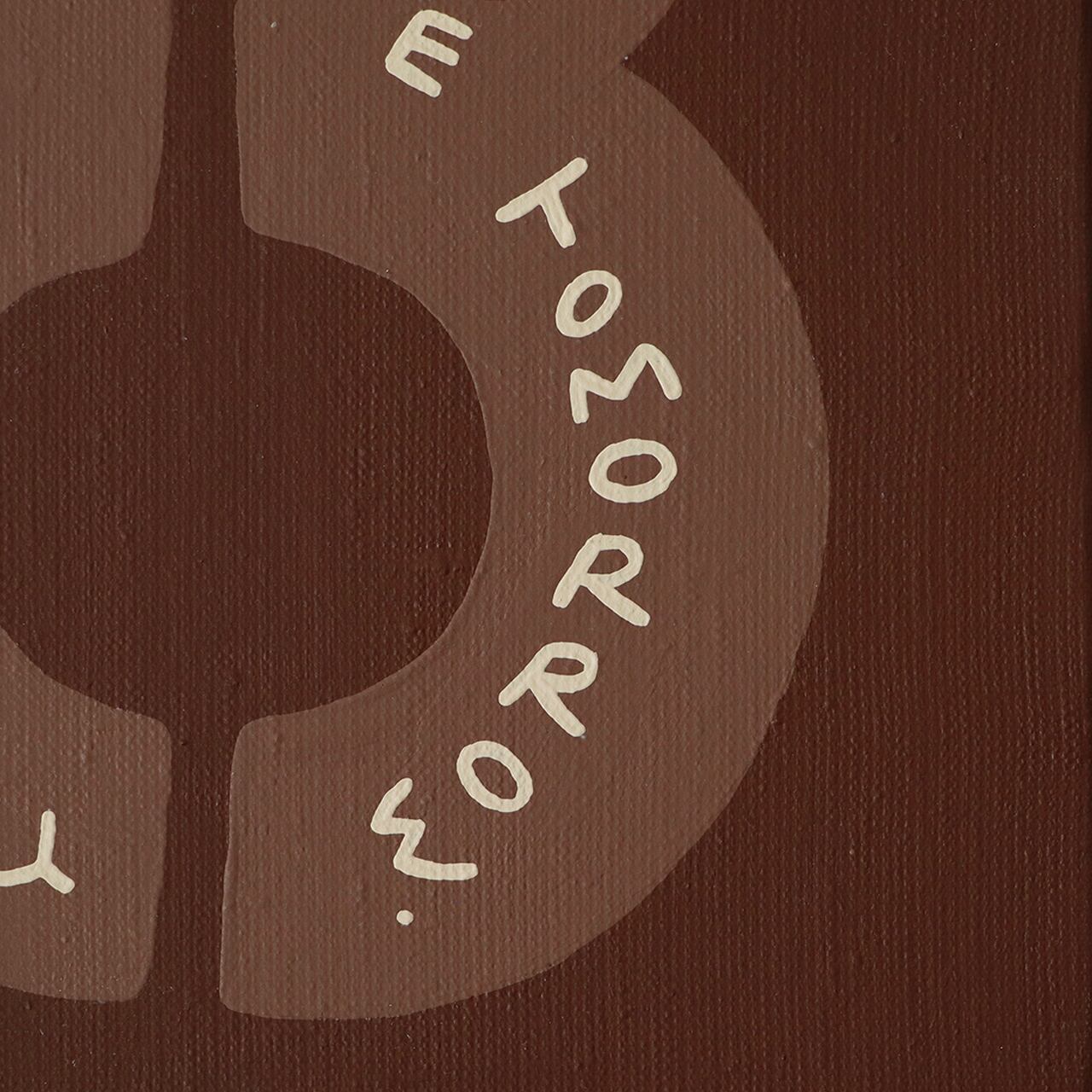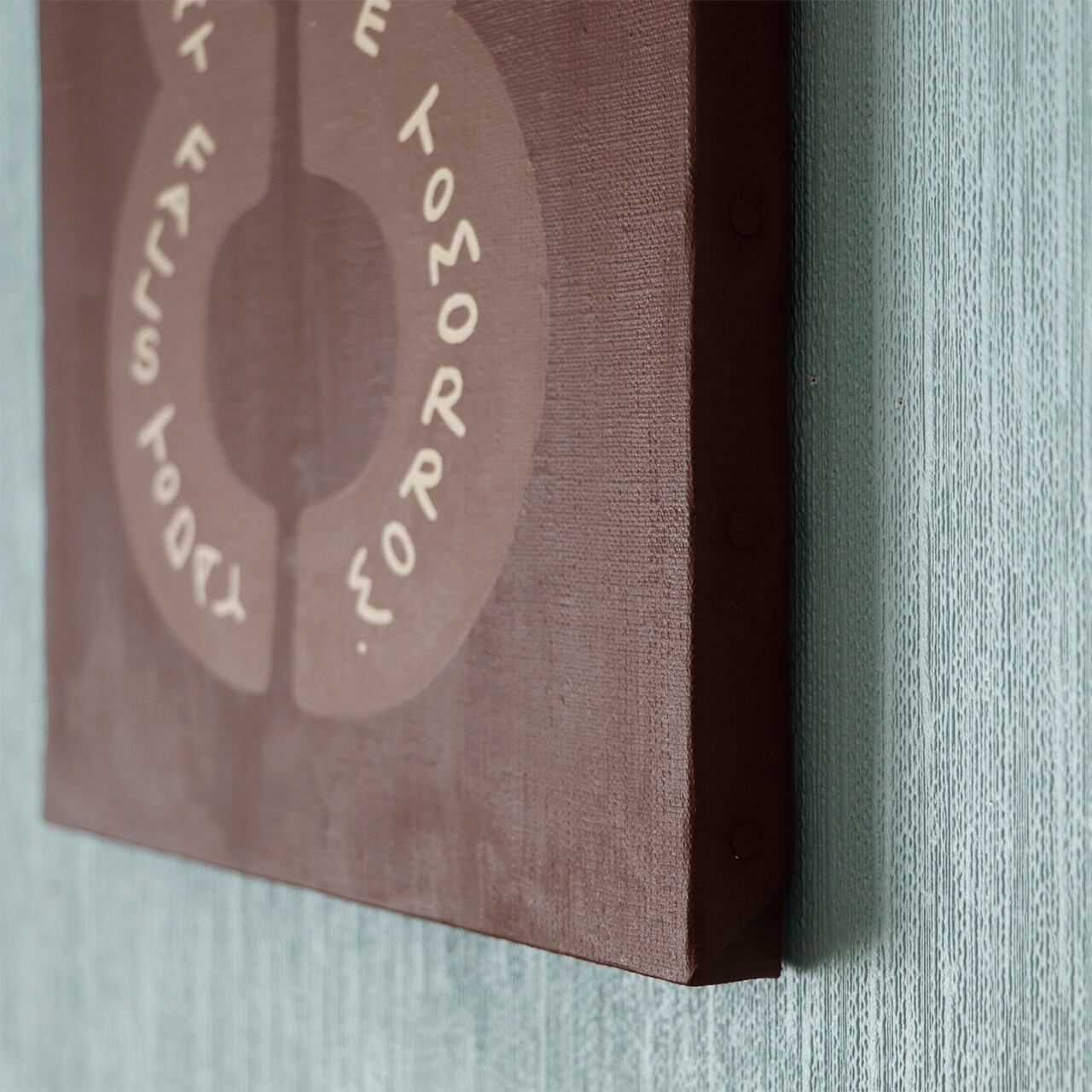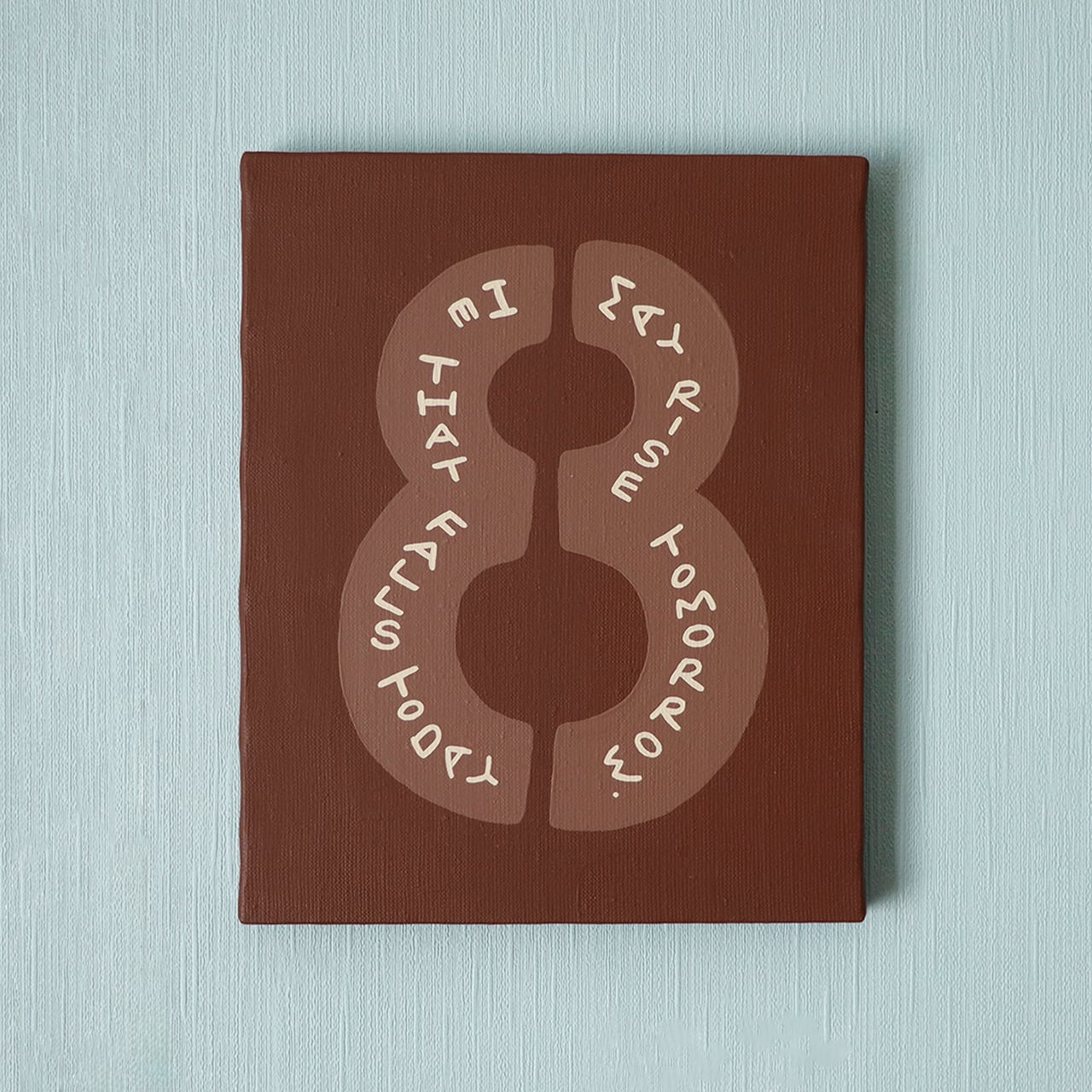
He that falls today may rise tomorrow
直訳だと「今日倒れた人は明日は立ち上がるかもしれない」
日本語のことわざに当てはめるなら「七転び八起き」
フレーズ自体には「8」は入っていませんが、
七転び八起きから取って数字の「8」をモチーフにしています。
今日よりも明日、転んだら起き上がりたい。
へこたれそうな時にオススメの作品です。